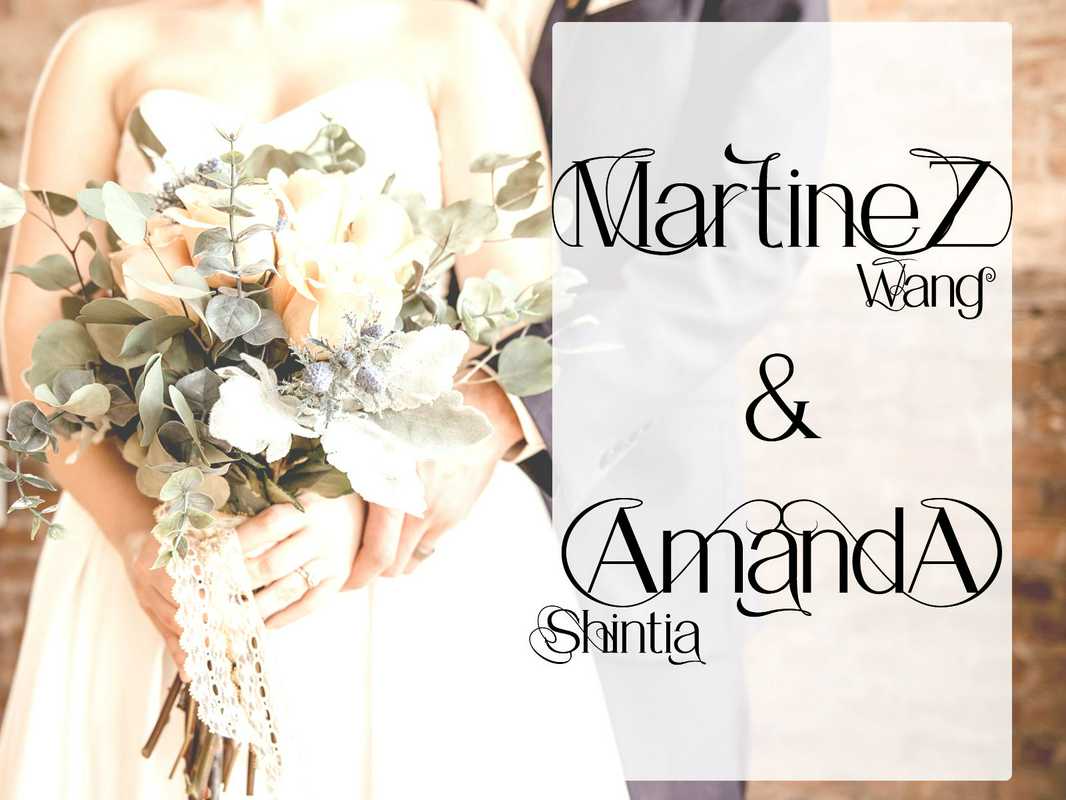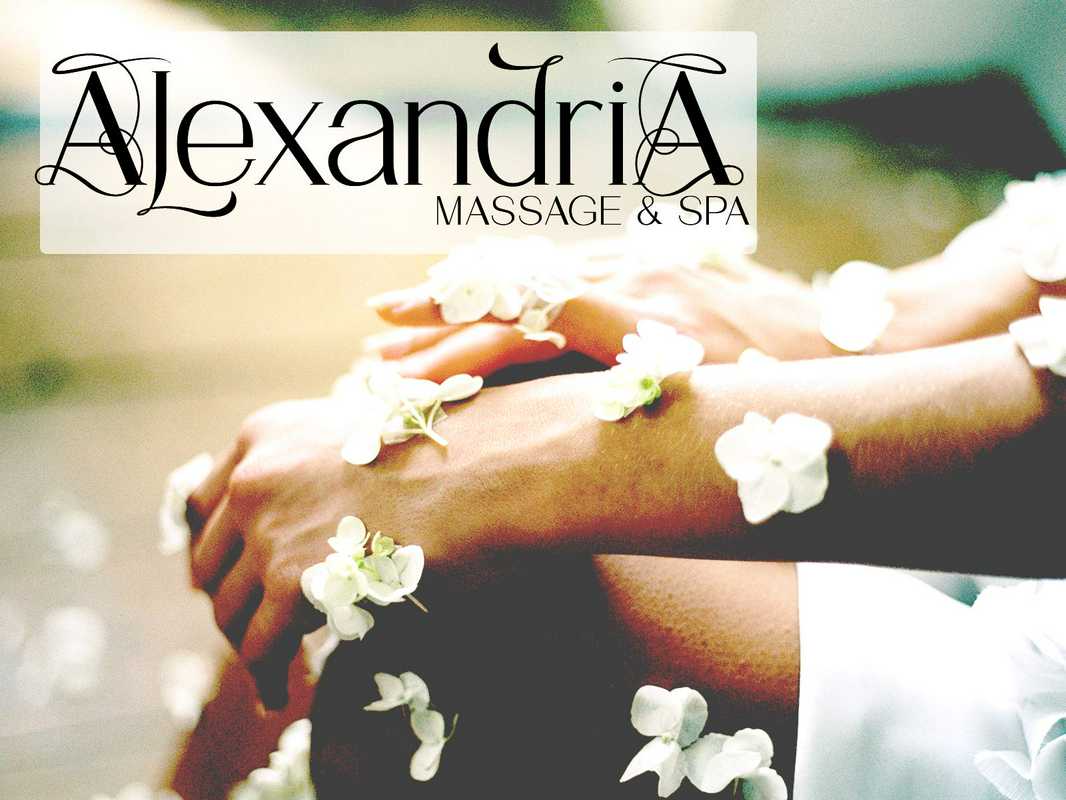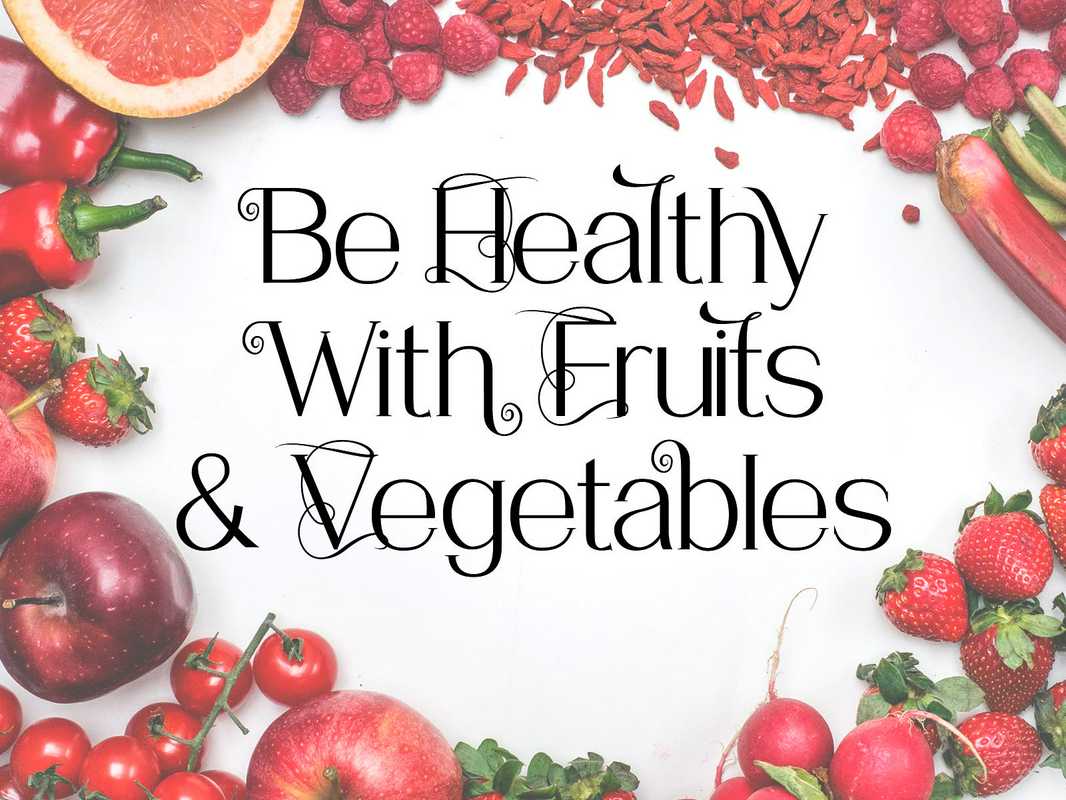
HalfBredisans&Serient采用简单的图形制作而成,具有独特和简约的触感,制作出美观和美观的字体,并由活页夹和更多字体替代品支持,以使您更轻松地探索您的设计风格,使用各种形式的可选样式,包括日志、海报、封面、主包装、t恤、名片、结婚卡等,因此,请尝试使用简单的图案制作半Bredissans&Serient,采用独特的、极简的触感,制作出美观、美观的字体,并使用活页夹和更多的字体替换品来支持您的设计风格,使您可以更轻松地探索您的设计风格,使用各种形式的替代风格,包括杂志、海报、封面、主包装、t恤、名片、,婚礼卡片和更多,那又怎样?请听我说?